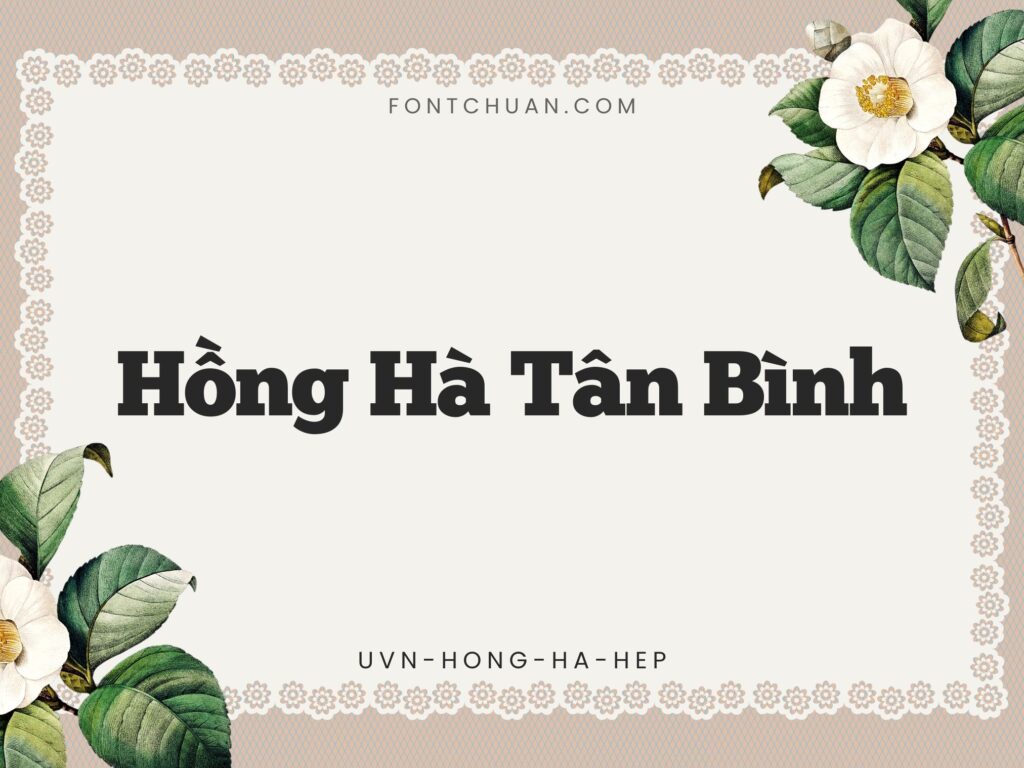
Font UVN Hong Ha Hep Việt Hóa
UVN Hồng Hà Hẹp là biến thể condensed của font UVN Hồng Hà, giữ nguyên tinh thần truyền thống nhưng được tinh chỉnh để phù hợp với không gian hẹp hoặc bố cục dọc. Với cấu trúc nhỏ gọn và cao hơn thông thường, font này giúp tiết kiệm diện tích mà vẫn duy trì được vẻ trang trọng, cổ điển. Font này chỉ được sưu tầm và đăng bởi thành viên của Font Chuẩn, nhằm phục vụ các nhu cầu thiết kế mang tính văn hóa, giáo dục hoặc truyền thông có giới hạn không gian hiển thị.
Thiết kế UVN Hồng Hà Hẹp thuộc nhóm serif condensed, các chân chữ rõ nét, đường nét thanh mảnh và dày dặn đan xen hợp lý. Font rất thích hợp cho tiêu đề báo chí, tiêu đề tài liệu, bìa sách hoặc banner truyền thông. Ngành nghề phù hợp gồm giáo dục, quảng cáo, công nghệ, bất động sản, ẩm thực. Các sự kiện phù hợp là ngày Nhà giáo, lễ hội, Tết và Trung thu.